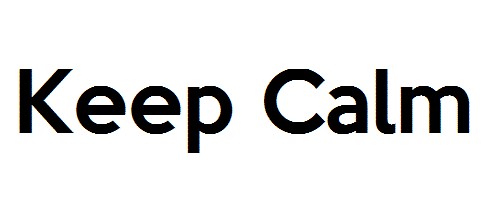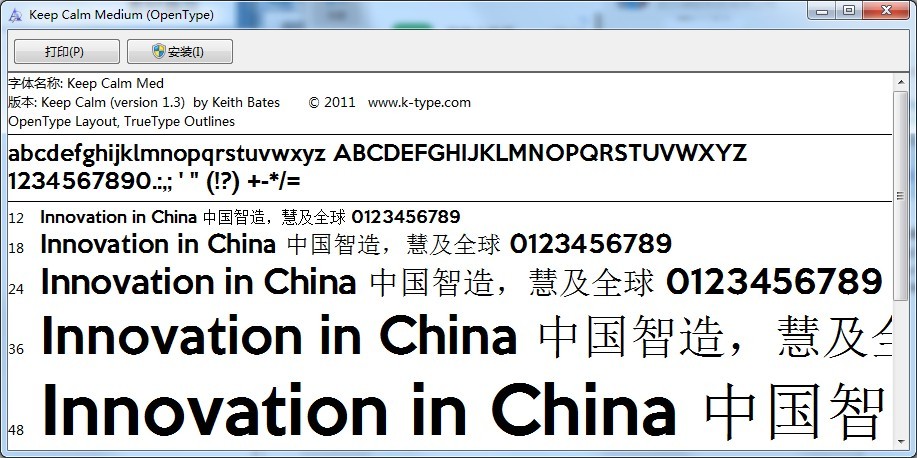
keep calm medium ttf字體效果偏粗,適用于正文當(dāng)中的英文字體,面對(duì)市面上如此繁瑣的英語(yǔ)字體,不同樣式的字體都有著其獨(dú)有的豐富,這款字體在常見(jiàn)的樣式上又多了些許藝術(shù)設(shè)計(jì),需要的用戶可以來(lái)下載試用。
keep calm是一款工整大方的英文字體,該字體工整、規(guī)范,可以廣泛地應(yīng)用于各類(lèi)廣告設(shè)計(jì)、PPT設(shè)計(jì)、海報(bào)制作、影視設(shè)計(jì)以及網(wǎng)頁(yè)設(shè)計(jì)等領(lǐng)域。